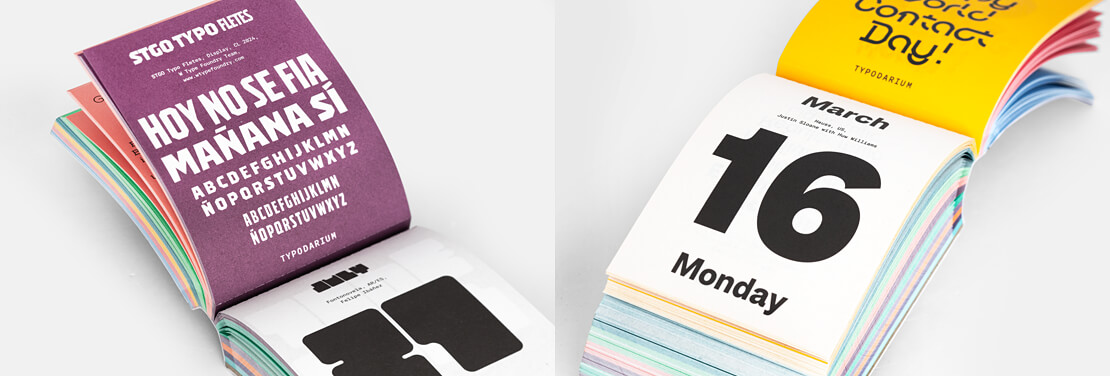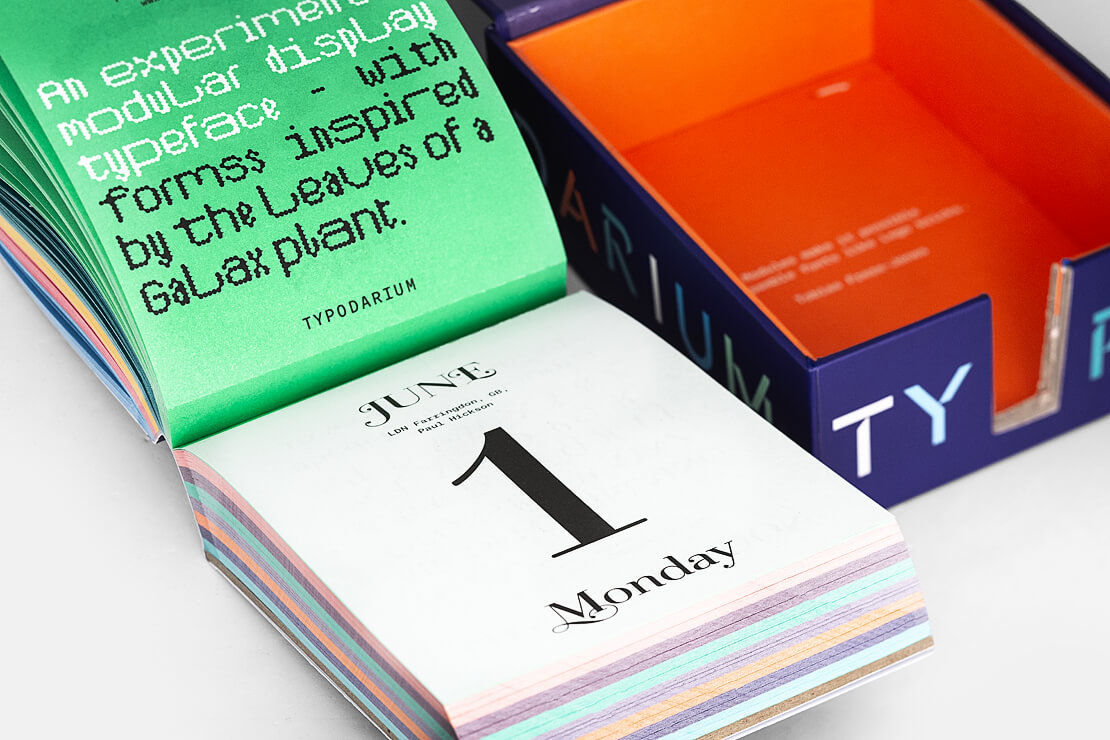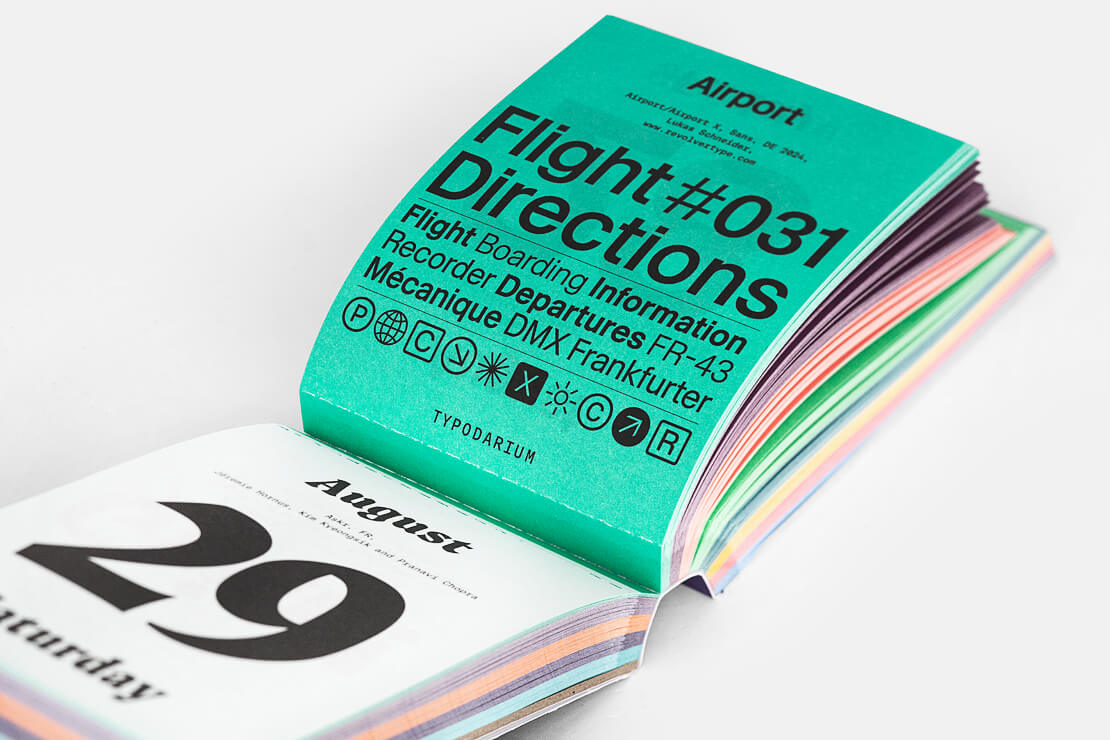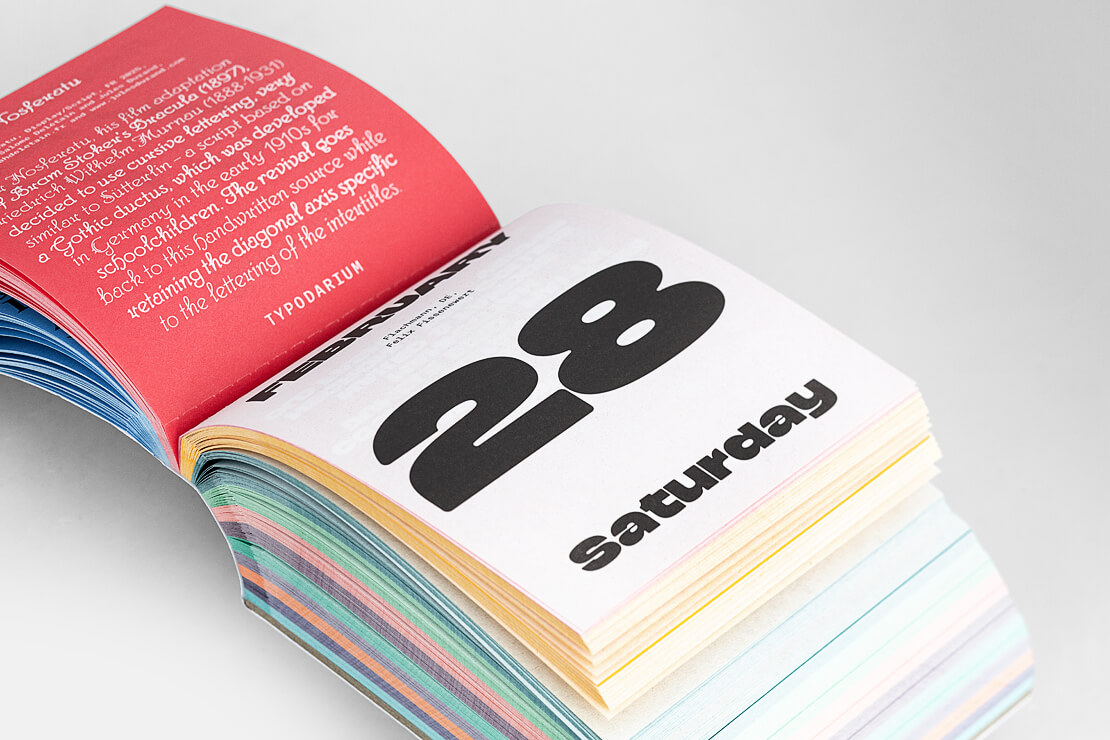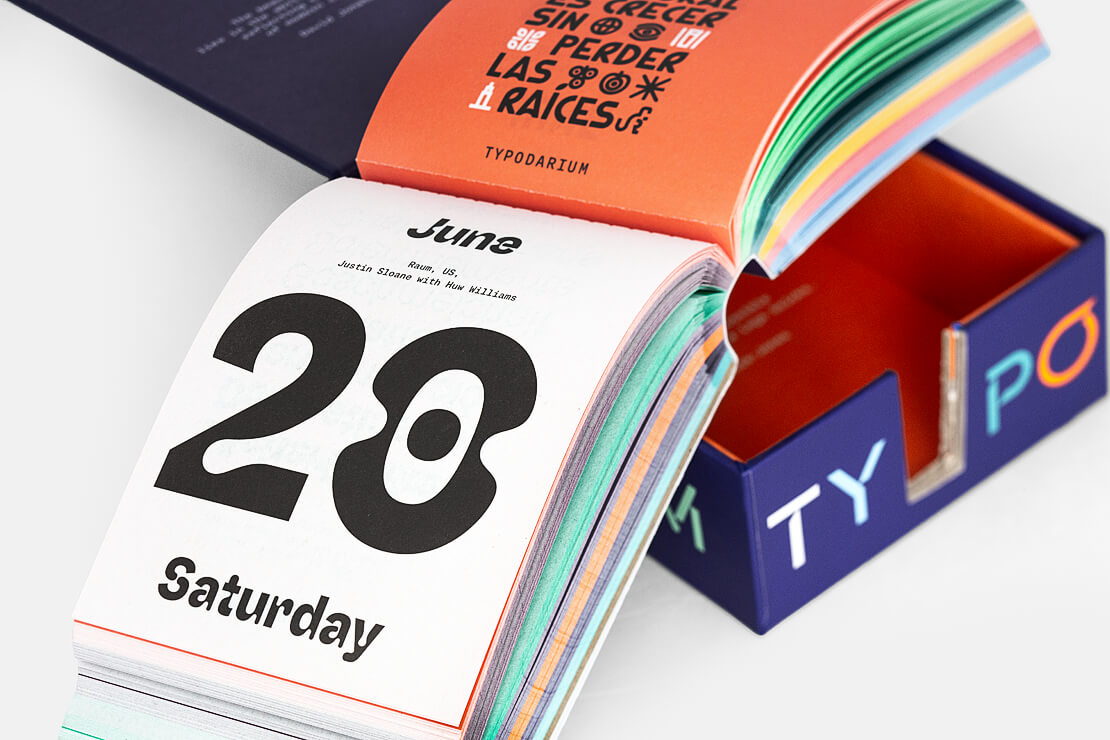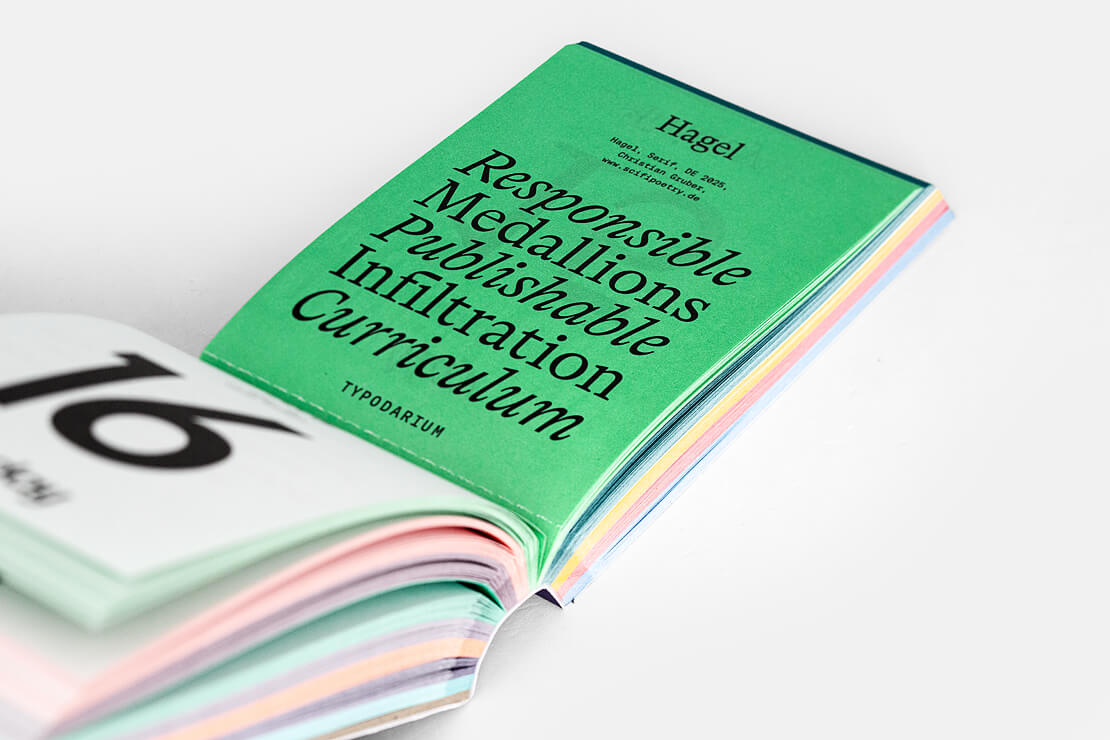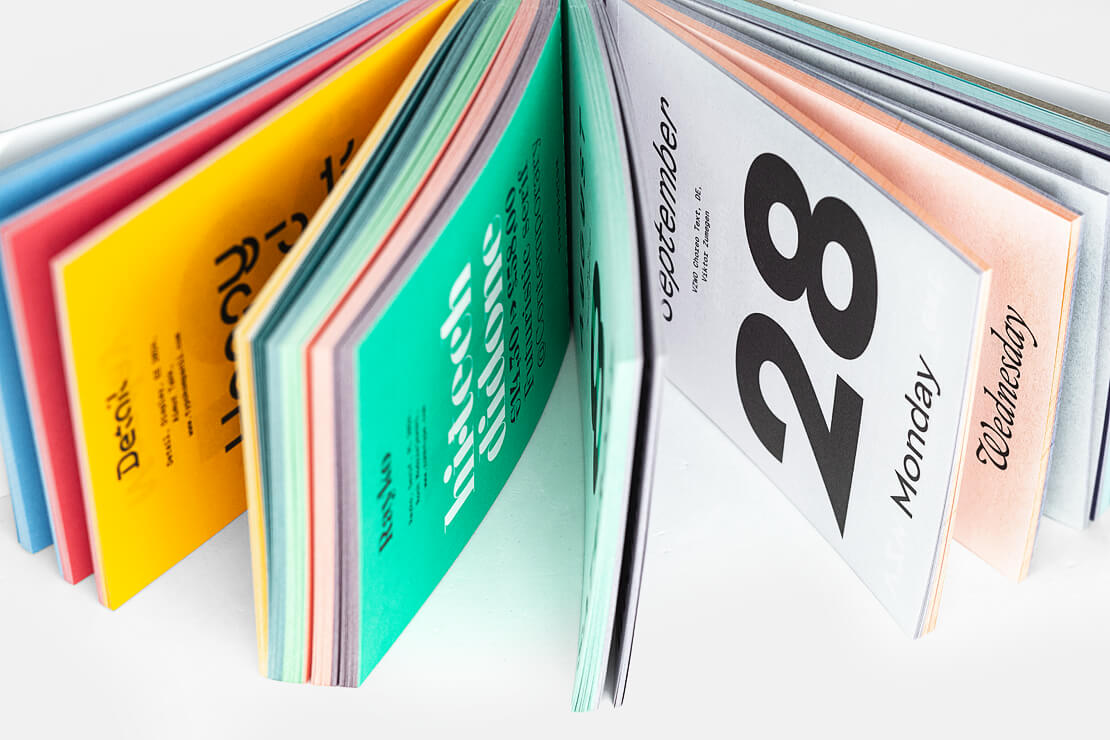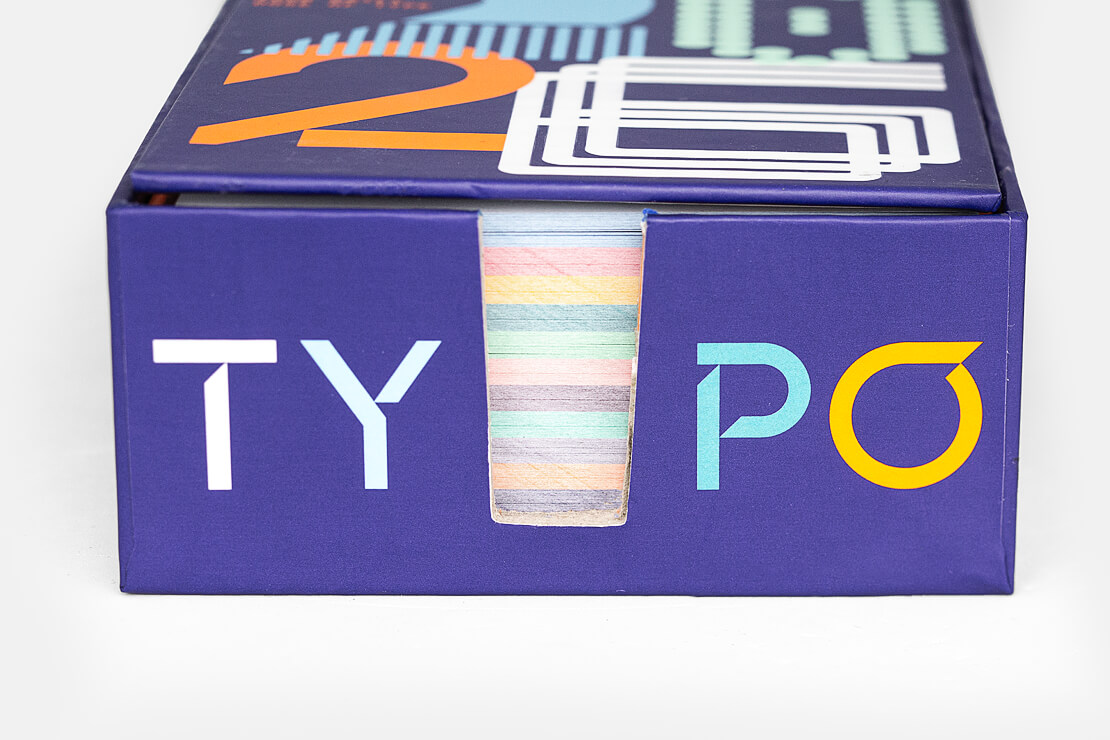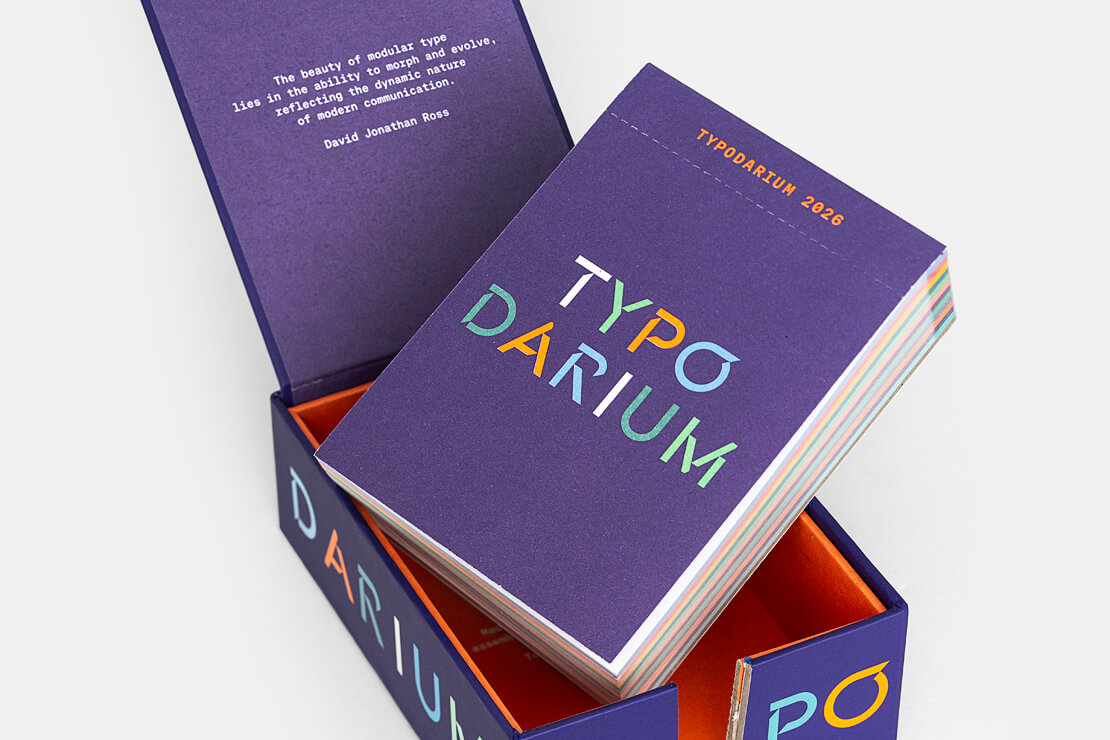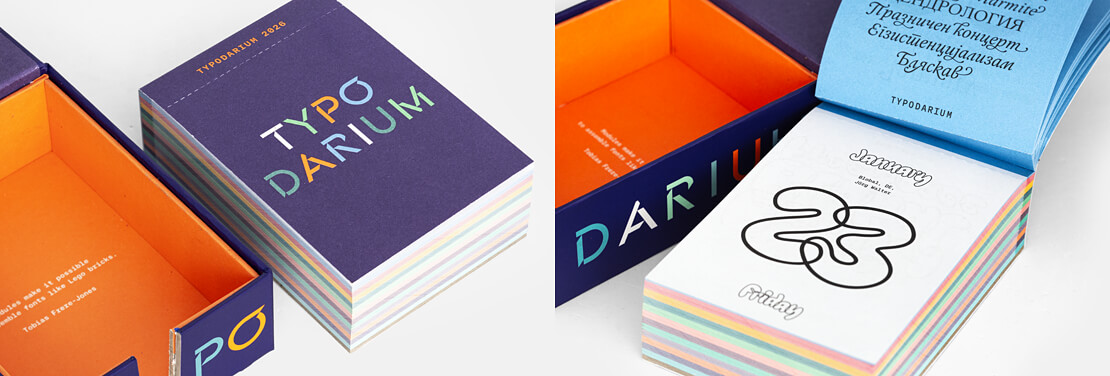
Typodarium 2026 erschienen
Das »Typodarium 2026« ist da und bringt erneut eine kuratierte Auswahl frischer Schriften direkt auf den Schreibtisch. Die Herausgeber Raban Ruddigkeit und Lars Harmsen präsentieren im typografischen Abreißkalender 365 Fonts für das Jahr 2026.
Typodarium 2026
Abreißkalender mit abwechslungsreichen Schriften
Als Trendradar und Inspirationsquelle bündelt das »Typodarium 2026« Entwürfe aus der internationalen Type-Szene. Die Bandbreite reicht von markanten Displayfonts bis hin zu auf Lesbarkeit optimierte Textschriften. Jede Kalenderseite zeigt eine andere Schrift. Zudem liefern Kurztexte auf der Rückseite zusätzliche Informationen zu Entstehung, Designerinnen oder Designer sowie Entstehungsjahr.
Typodarium Kalender 2026
365 Schriften im »Typodarium 2026«
In diesem Jahr versammelt der Kalender 365 Schriften von 330 Kreativen aus 39 Ländern. Die Sonntage greifen jeweils bestimmte Themen der Schriftgestaltung auf und setzen Akzente, die Entwicklungen im Typedesign bündeln und vergleichbar machen. So wird der tägliche Abriss zugleich zur Dokumentation aktueller Strömungen.
Kalenderseiten aus Typodarium 2026
Format und Ausstattung
Das Format bleibt mit 8,5 × 12 cm kompakt. Enthalten sind 384 Tagesblätter in zwölf Farbvarianten (beidseitig bedruckt). Jede Ausgabe steckt in einer neu konstruierten, vierfarbig bedruckten Sammelbox, partiell mit glänzendem, erhabenem UV-Spotlack veredelt. Diese eignet sich zur Archivierung der abgerissenen Blätter.